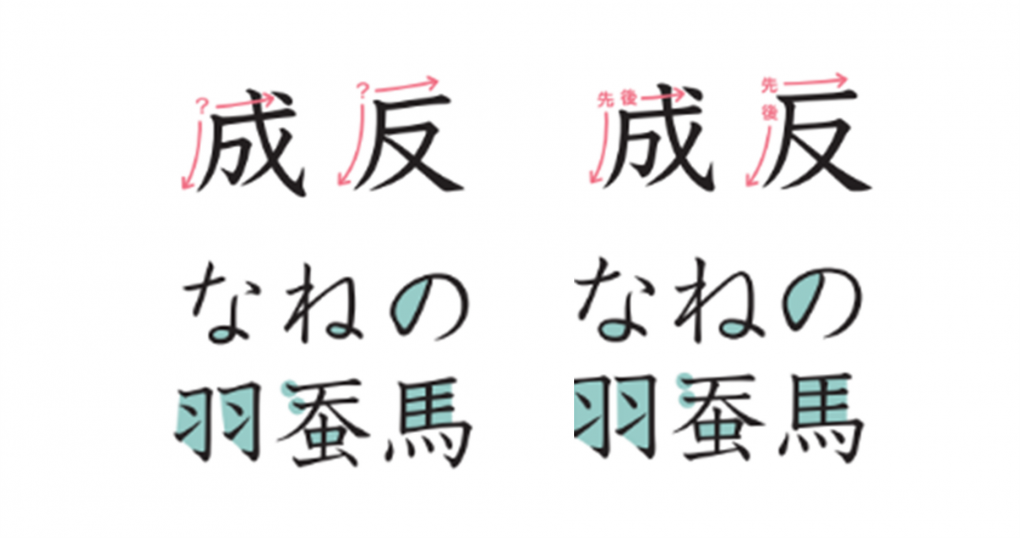
‘보기 쉬운’ 폰트, 이렇게 만들었어요
이와타 UD 폰트 시리즈 : ‘아름다운’ 폰트보다, ‘보기 쉬운’ 폰트
이와타의 UD 폰트 시리즈는 목적별로 구분되어 있어요. 「UD고딕(Gothic)」은 전자제품 표시용으로 개발된 누가 봐도 보기 좋은 폰트, 「UD마루고딕(MaruGothic)」은 여성과 어린이를 타깃으로 분위기가 부드럽고 보기 좋게 개발한 폰트, 「UD명조(Mincho)」는 서적이나 뉴스레터 등에서 사용되는 폰트에 유니버셜 디자인의 요소를 더해 보기 쉽게 만든 폰트랍니다.
교과서 제작에도 선택 받았어요. 「이와타 신교과서체」
「신교과서체(NewKyoukasho)」도 앞서 소개한 UD 폰트 시리즈 중 하나라고 해도 좋을 것 같아요. 기존 교과서체에 UD 폰트의 노하우를 담은 폰트라고 할 수 있는데요, 이 폰트는 기존 교과서체와 비교하여 다음과 같은 차이가 있습니다.
① 쓰는 순서를 파악하기 쉬운 것
② 붓이 아닌 경필(펜이나 연필)의 느낌을 나타낼 것
③ 글자의 곡선이 크게 디자인되어 있을 것
어떤가요? 결과적으로 한 글자 한 글자가 커 보이기 때문에 글자의 구성을 알기 쉬워졌죠? 특히 가로줄이 수평에 가까워져서 디지털 환경에서도 보기 편해졌다는 장점도 있어요. 🙌